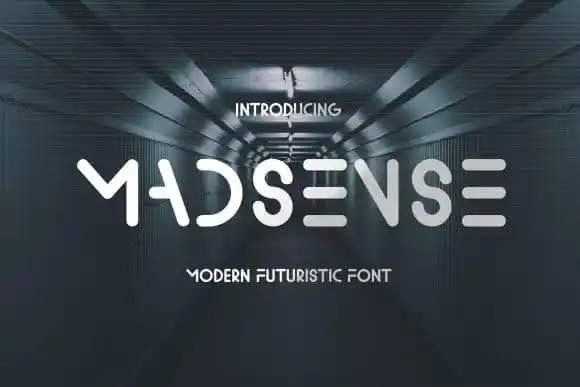
A Madsense Display Font é uma tipografia sans serif que traz à tona uma fusão de retrofuturismo e minimalismo contemporâneo. Criada pelo designer TypeFactory, esta fonte tem um amplo domínio, ideal para logos simplistas e marcas de lojas. O design digital emoldura sua estrutura, destacando-se para aplicações como nomes e títulos de livros, jogos digitais, slogans modernas, e temas de interiores tecnológicos. Com um toque inovador que traz vida ao seu uso, a Madsense é uma escolha perfeita para quem busca unir elementos do passado com o futuro na sua identidade visual.